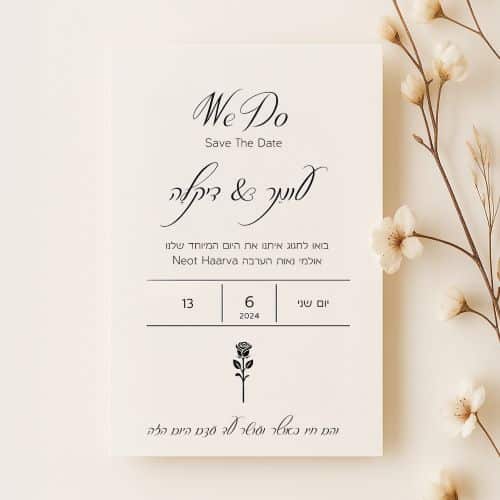
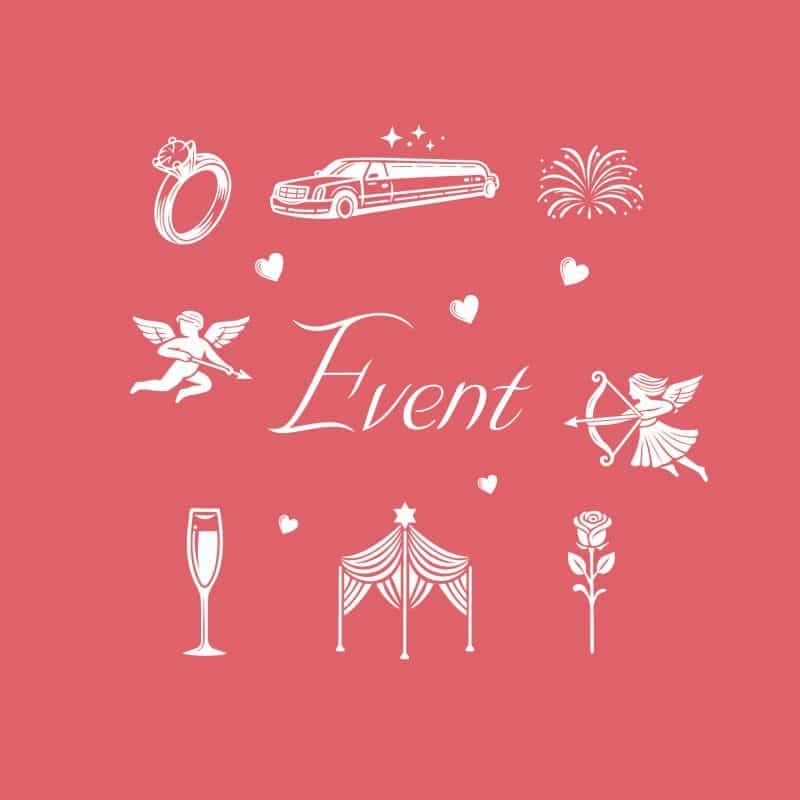
אירועים מיוחדים דורשים עיצוב שמרגש, מפתיע, ומדבר ישר ללב. בין אם מדובר בחתונה אינטימית, בר מצווה חגיגית, השקה נוצצת או ערב התרמה יוקרתי – העיצוב הוא לא רק תפאורה שמסביב, אלא הדרך שבה אתם מספרים את הסיפור שלכם. הוא קובע את הטון, את האווירה, ואת הזיכרון שיישאר.
בתוך כל הסיפור הזה מסתתר גיבור שקט אך עוצמתי במיוחד: הפונט. בחירה מדויקת של פונט יכולה להפוך כל הזמנה פשוטה ליצירת אמנות, וכל שלט סטנדרטי להצהרה מרגשת. במדריך הבא נלמד איך לבחור את הפונט המתאים לכל סגנון של אירוע – מהודר, אישי או קליל.
לפני שבוחרים פונט, חשוב לשאול: מה הסגנון של האירוע? רשמי או קליל? רומנטי או טכנולוגי-חדשני? כפרי או מודרני? ואז נתאים את הפונט באופן שמתכתב עם סגנון האירוע. כך פונט אלגנטי עם קווים נקיים יתאים לאירוע ערב יוקרתי, ואילו שפונט עם טאץ’ רטרו יכול לשדר חמימות ואופי אישי.
ובעוד שפונט מודרני וגיאומטרי יתאים לאירוע טכנולוגי או קונספט חדשני, כך פונט רך ועגול יכול להחמיא לאירועי ילדים או חגיגות בסגנון ביתי ומשפחתי. התאמת הפונט לאופי האירוע תעזור לכם להעביר את המסר הנכון כבר מהרגע הראשון.
הפונט לא רק נראה יפה (או פחות יפה במקרה של בחירה פחות נכונה) – פונט הוא כזה שמשדר תחושה. הוא יכול להיות שמח, חגיגי, סולידי, מלא סטייל או כל דבר אחר.
בין אם מדובר בכותרת על שלט, טקסט בהזמנה או מיתוג על המזכרות – לכל אות ואות יש משקל רגשי. ההמלצה החד-משמעית שלנו היא: בחרו פונטים שיוצרים את התחושה המדויקת שאתם רוצים שהאורחים ירגישו כשהם נחשפים לעיצוב.
בשוק העיצוב היום יש מגוון רחב של פונטים בעברית – חלקם קלאסיים, אחרים חדשניים, ויש כאלה שמשלבים בין ישן לחדש בצורה מפתיעה. הבחירה הנכונה תעשה את כל ההבדל.
אירוע חד-פעמי הוא בעצם גם סוג של מותג זמני – בדרך כלל יש לו לוגו, שפה גרפית, קונספט עיצובי ועוד. זו הסיבה שבגללה יצירת מותג בעזרת טיפוגרפיה רלוונטית גם כאן.
פונט אחד שנבחר בקפידה ואחרי שיקול דעת, ועובר כחוט השני בין כל המוצרים הקשורים לאירוע: ההזמנות, השילוט, המסכים והמתנות – יוצר שפה אחידה, מכובדת ובלתי נשכחת.
ולמי מכם שמעוניין ליצור משהו ייחודי ממש מהבסיס, יש היום סט כלים לקליגרפיה, בין אם דיגיטליים ובין אם כלים ידניים. הם יכולים להעניק מראה אותנטי ומקורי שלא רואים בכל אירוע.
לסיום, הטיפוגרפיה היא בעצם הלב של העיצוב. כשבוחרים את הפונט הנכון, כל פרט – החל מההזמנה, עבור דרך כל המוצרים וכלה בשלט באולם – כל אחד מהם הופך לחלק מהרמוניה אחת ברורה, מדויקת ומרגשת.
הפונט הוא זה שמגדיר את הטון של העיצוב – בדיוק כמו מוזיקה ברקע. הוא קובע אם האירוע ייראה קלאסי, צעיר, רשמי או כפרי, וכן הלאה. אין לזלזל בתפקיד המהותי של הפונט בהעברת המסר וקביעת האווירה.
מומלץ לבחור פונט אחד דומיננטי (לכותרות) ועוד פונט משלים (לטקסטים). חשוב לוודא שיש ביניהם הרמוניה ולא תחרות.